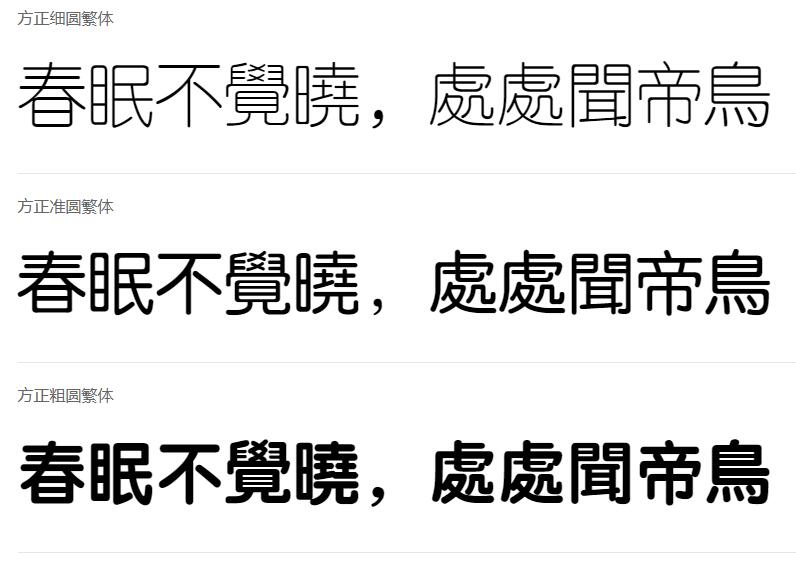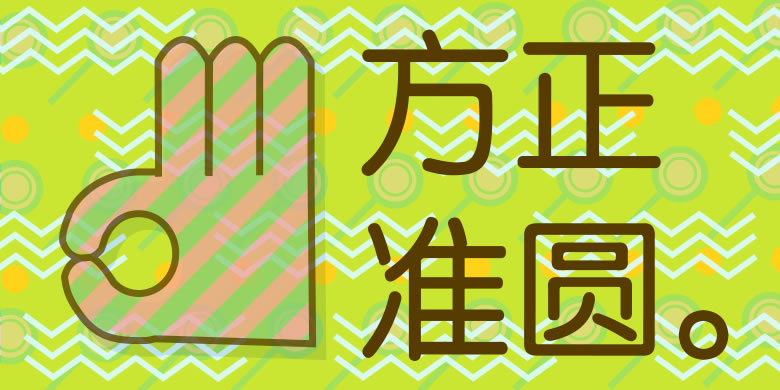
Font name:方正圆体系列
字体介绍:
方正圆体家族的中宫宽松,字面大,起笔处与收笔处为圆形,折笔处呈圆弧状。方正圆体家族的字形风格舒展柔和,适用于女性、儿童和生活用品类的宣传册和包装设计等。方正圆体家族包括3款字重,其中方正粗圆笔画厚重饱满,适用于标题;方正准圆笔画粗细适中,适用于正文排版;方正细圆笔画纤柔,也适用于正文排版。
设计师: 方正字模部
分类:黑体